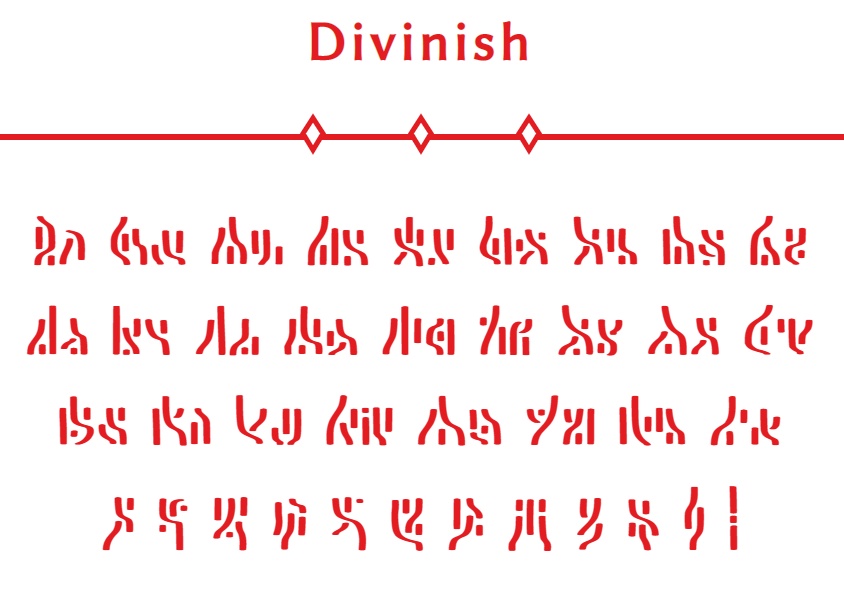
Fantasy Font | Divinish
ファンタジー系のTRPG等で使うことを想定して制作したフォントです。 はるか昔、神々が世界を統治ていた平穏な時代の文字を意識して制作しました。 Euglianと同じく魔法陣や石碑などに使うと良さそうかも知れません。 ---- 「Fantasy Font シリーズ 全6書体全部入りセット」をご購入すると格安で入手できてお得です。ぜひこちらをどうぞ! https://soya-workshop.booth.pm/items/4766747
使用文字見本
Aa Bb Cc Dd Ee Ff Gg Hh Ii Jj Kk Ll Mm Nn Oo Pp Qq Rr Ss Tt Uu Vv Ww Xx Yy Zz 1 2 3 4 5 6 7 8 9 0 . ,